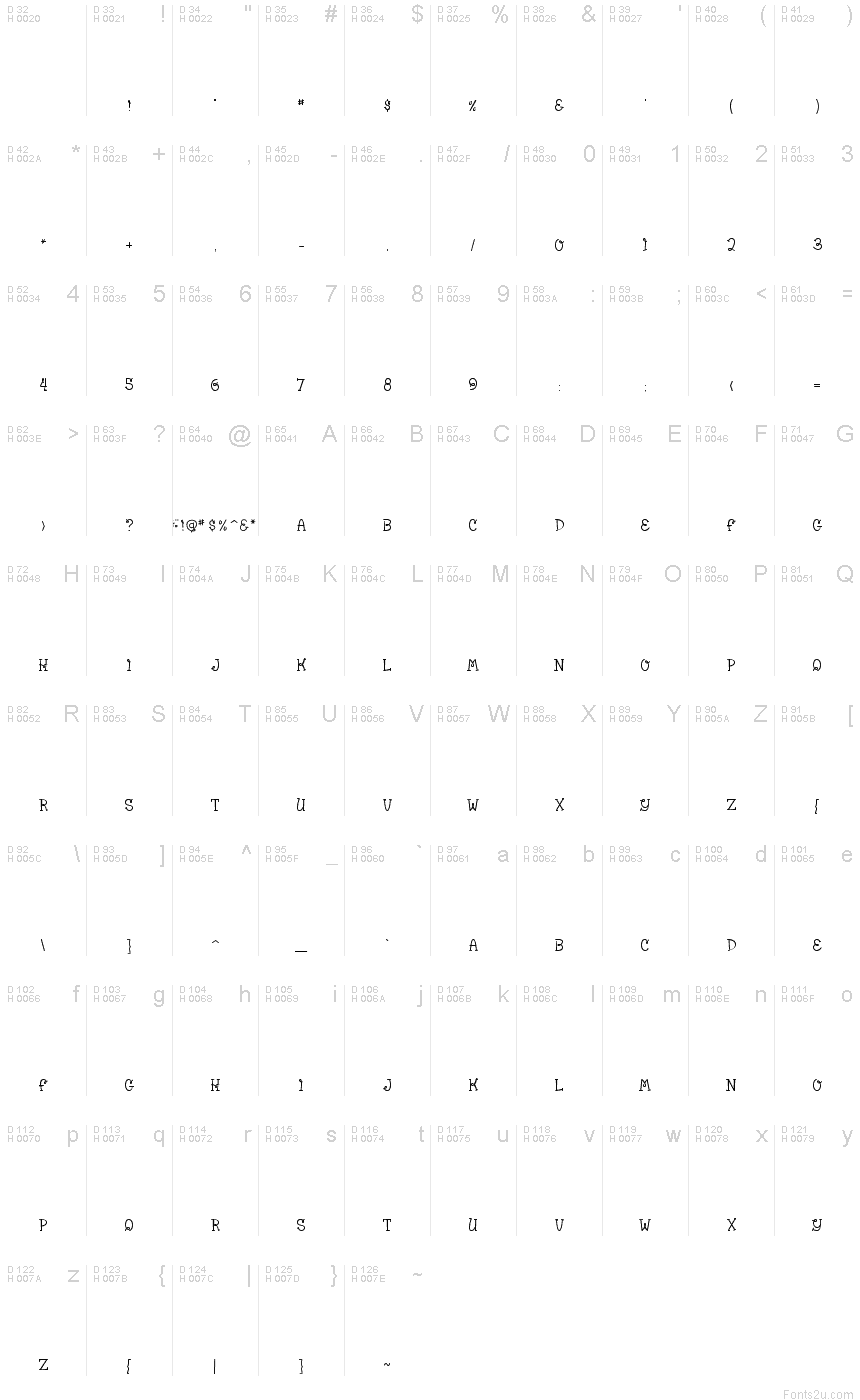
يُعد خط Bumble Bee BV من Blue Vinyl Fonts خطاً يدوياً مجانياً يتميز بسحر مرح يشبه قصص الأطفال. تلتف الحروف الطويلة والضيقة لتشكل خطافات وحلقات لعوبة، تشبه رسومات أقلام التحديد، بينما يحافظ سمك الخط الموحد على وضوح القراءة والطابع الودود. يتمتع الخط بطاقة خفيفة ومرحة تجعله مثالياً لأي تصميم ممتع أو موجه للأطفال.
باستخدام Bumble Bee BV، يمكنك إضافة لمسة دافئة إلى أغلفة كتب الأطفال، وملصقات الفصول الدراسية، ودعوات أعياد الميلاد، وملصقات الأعمال اليدوية، وتغليف الألعاب، والمنشورات العائلية على وسائل التواصل الاجتماعي. يتألق هذا الخط المجاني عند استخدامه بأحجام كبيرة في العناوين مع دمجه بخط بسيط بلا زوائد (sans serif) ومستدير للنص الأساسي، مما يترك منحنياته المميزة ومسافاته الكبيرة تعبر عن نفسها بوضوح.